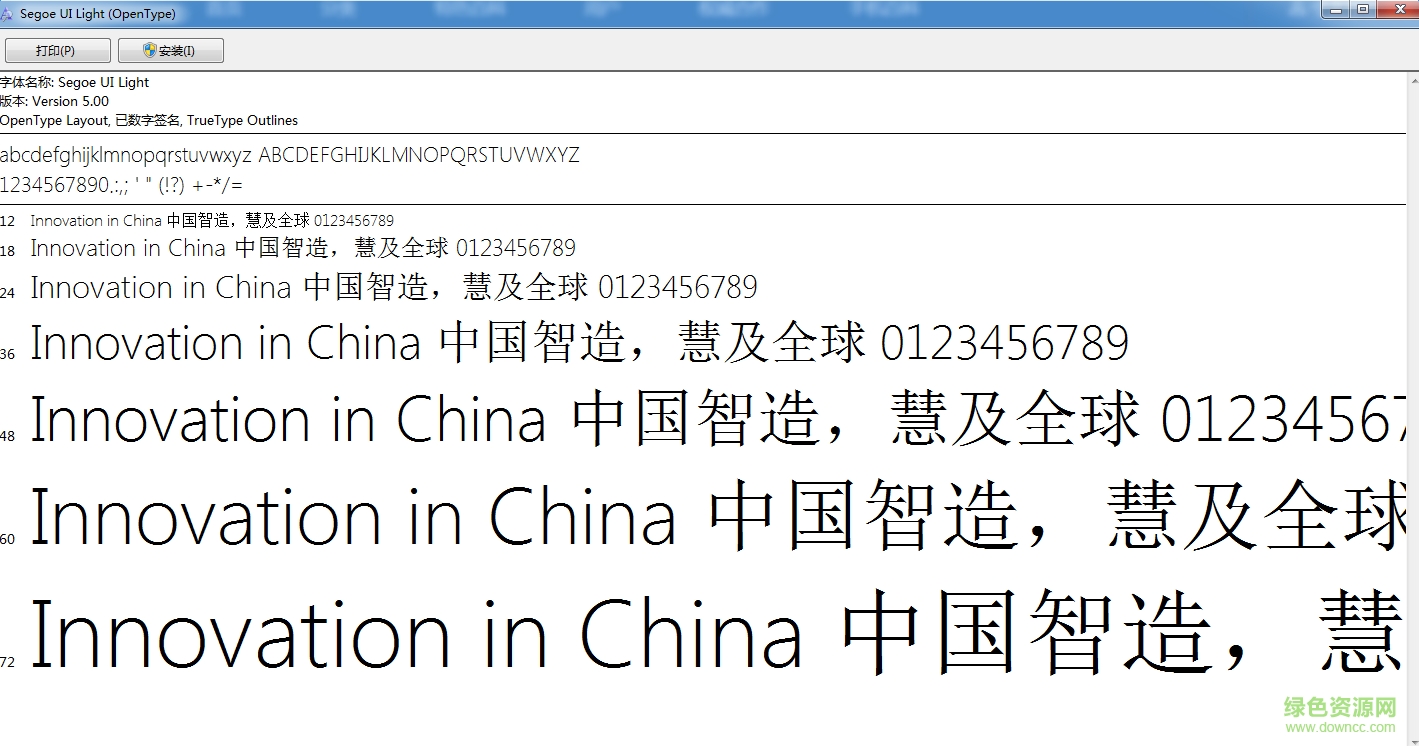
segoe ui light 8字體是一款常用于微軟用戶界面的西文無襯線體,該字體線條平滑美觀,結構嚴謹,空隙均勻,布白得當,看上去非常標準,歡迎大家下載!
Segoe UI和Tahoma一樣仍然是一款不等寬字體。Segoe UI 是Segoe商標下一系列(至少有27種)字體的一種,這個系列的其他字體包括品牌印刷字體的拓展 ,在微軟內部、廣告代理商使用。據微軟稱,新的Segoe UI字體利用了ClearType顯示技術的優(yōu)勢,比目前的系統(tǒng)字體更加現代化。